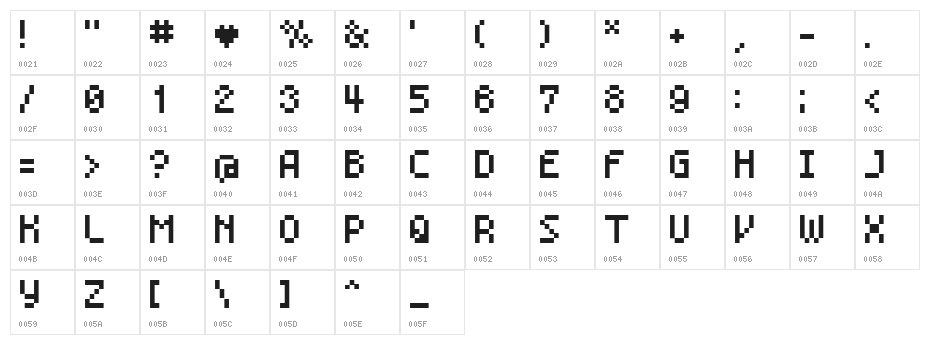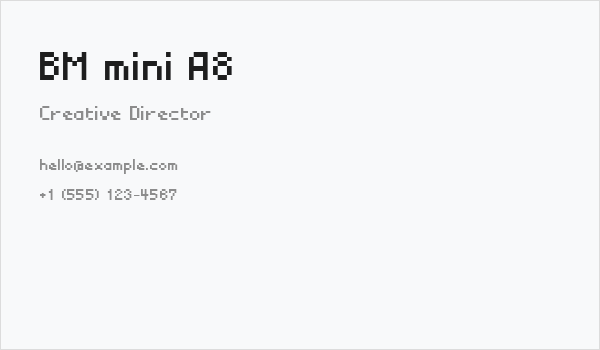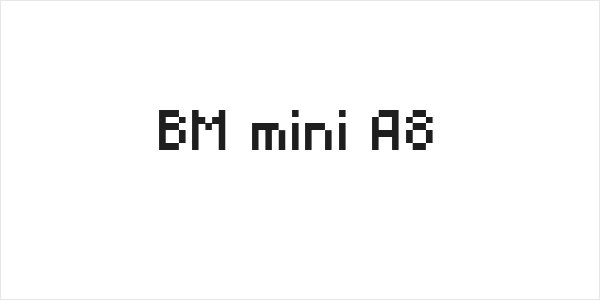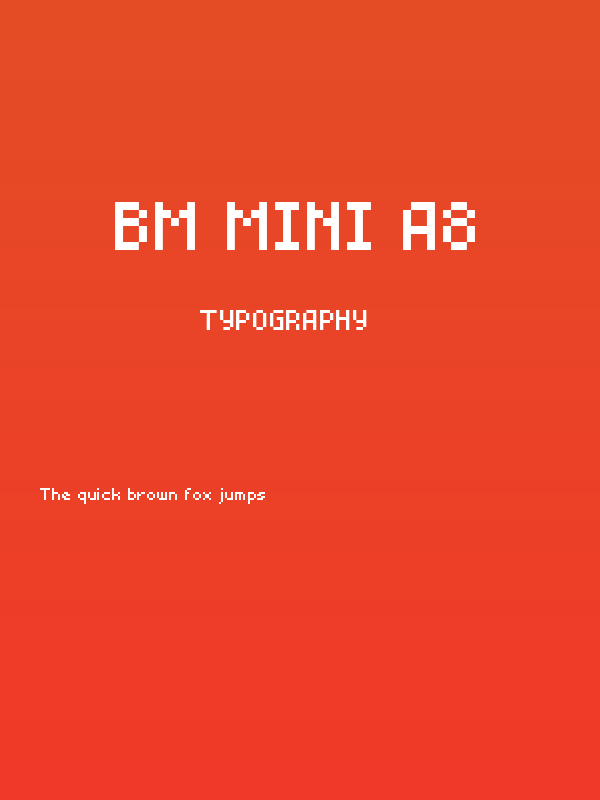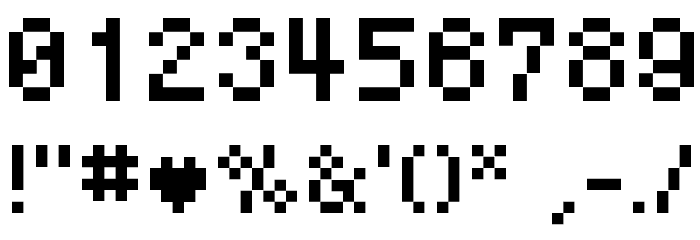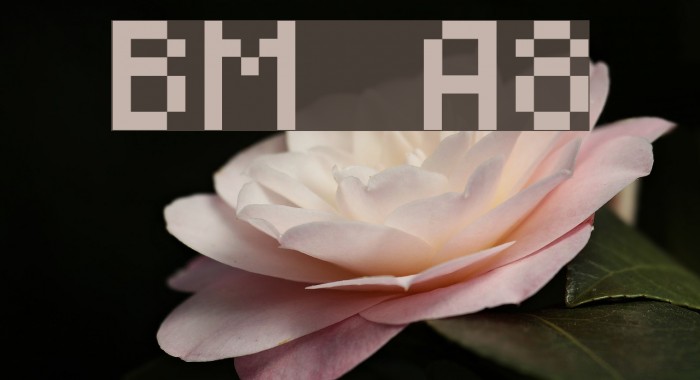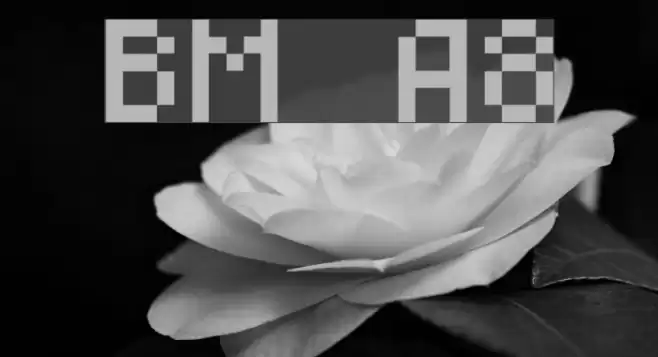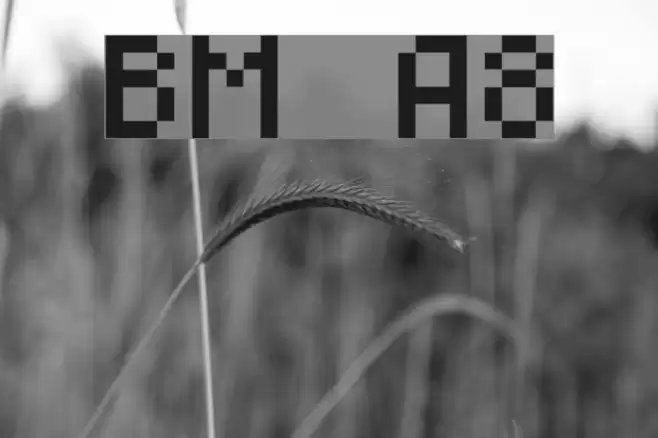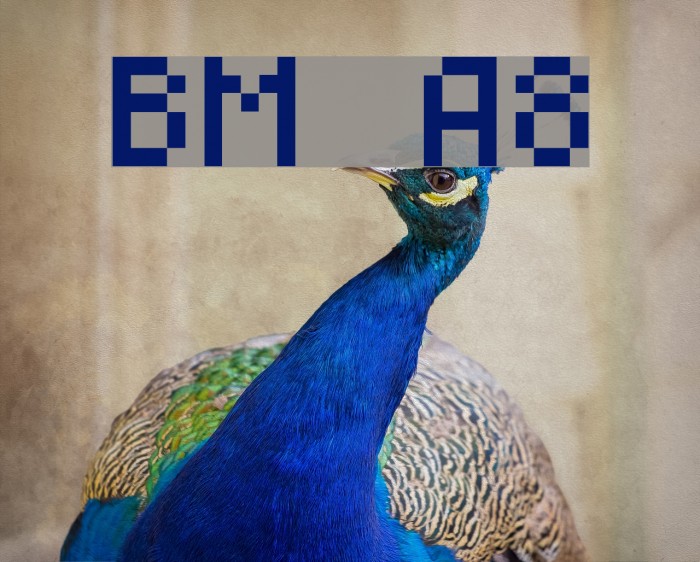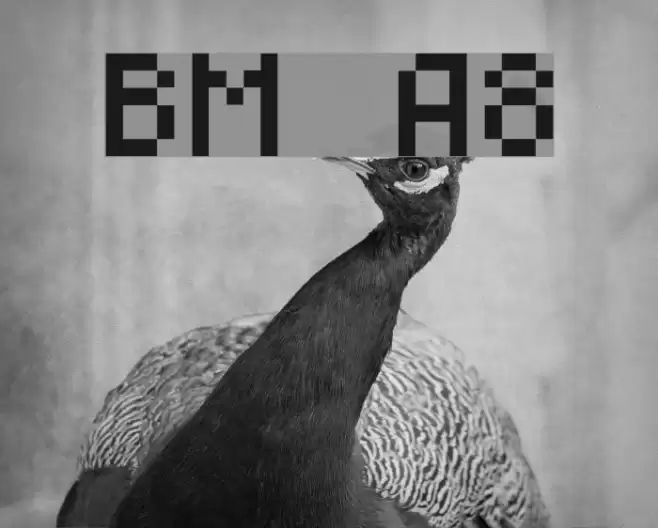
BM mini A8 Font
| Categorii | Pixel |
| Stil general | Retro, Digital |
| Caz de utilizare | Headlines, Logos, Digital Art |
| Proiecte propuse | Ideal for retro video game designs, digital art projects, and any creative work that seeks to evoke a sense of nostalgia for early computing and gaming eras. |